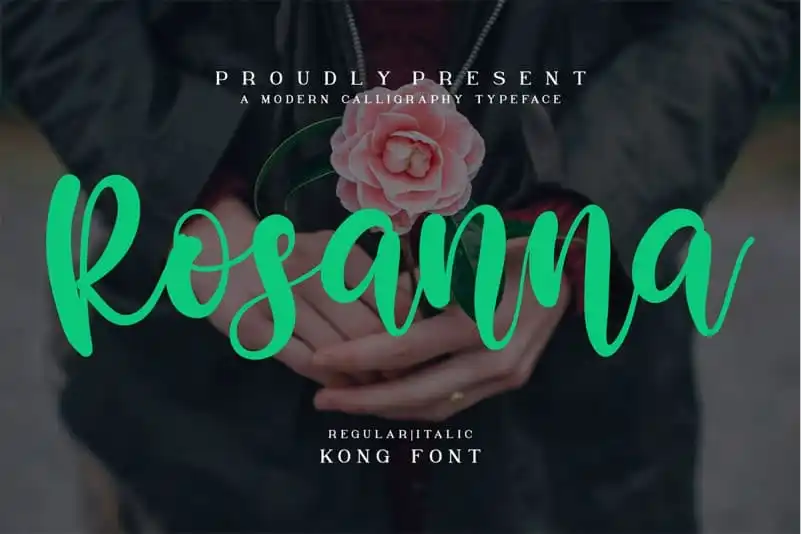
Rosanna Calligraphy Font – Download Grátis
A Rosanna Calligraphy Font é uma maravilhosa e eterna fonte escrita a mão. Ideal para criar logotipos impressionantes, marcações e citações. Cada letra tem um toque único e belo que fará sua criação brilhar ainda mais! Esta fonte é perfeita para logotipo, cabeçalhos de websites, design de moda e até mesmo cartões de casamento. Ela contém uma caixa completa de letras maiúsculas e minúsculas, um grande conjunto de pontuação, números e suporte multilíngue. A Rosanna Calligraphy Font é uma fonte perfeita para todas as suas necessidades de design gráfico, seja você criando um logo moderno ou reeditando cartões de Natal. Ela oferece uma experiência única e emocionante em qualquer tipo de projeto que você decida trabalhar. Não deixe essa bela fonte passar despercebida no seu próximo trabalho de design.